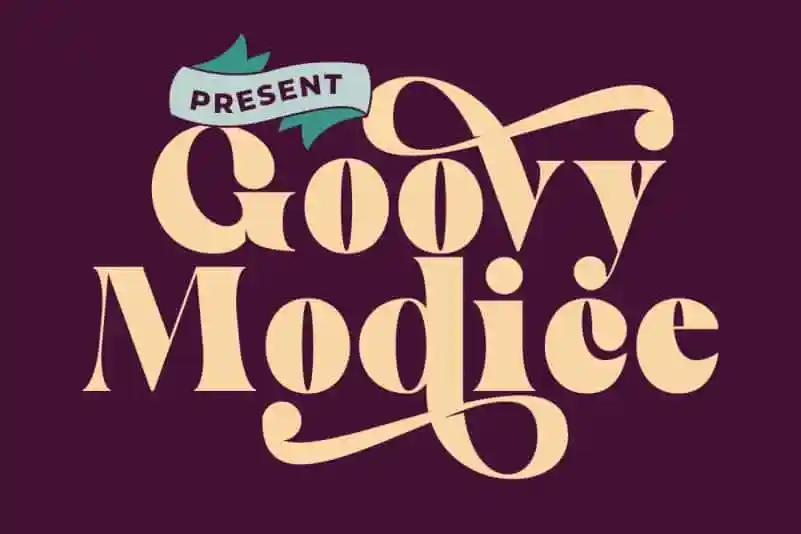
A Goovy Modice Serif é uma fonte de tipo que foi criada para ser alegre e confortável ao ler na tela digital. Seu toque refinado dá qualquer headline um aspecto elegante, tornando-a a escolha perfeita para editoriais modernas ou vintage. Este tipo foi meticulosamente projetado para ter ambas as curvas modernas e vintage, criando uma versatilidade incrível que pode ser facilmente combinada com uma enorme variedade de projetos. Seja você um designer que busca criar propostas inovadoras, a Goovy Modice oferece a oportunidade de fazer suas ideias se destacarem no design gráfico moderno e vintage ao mesmo tempo.